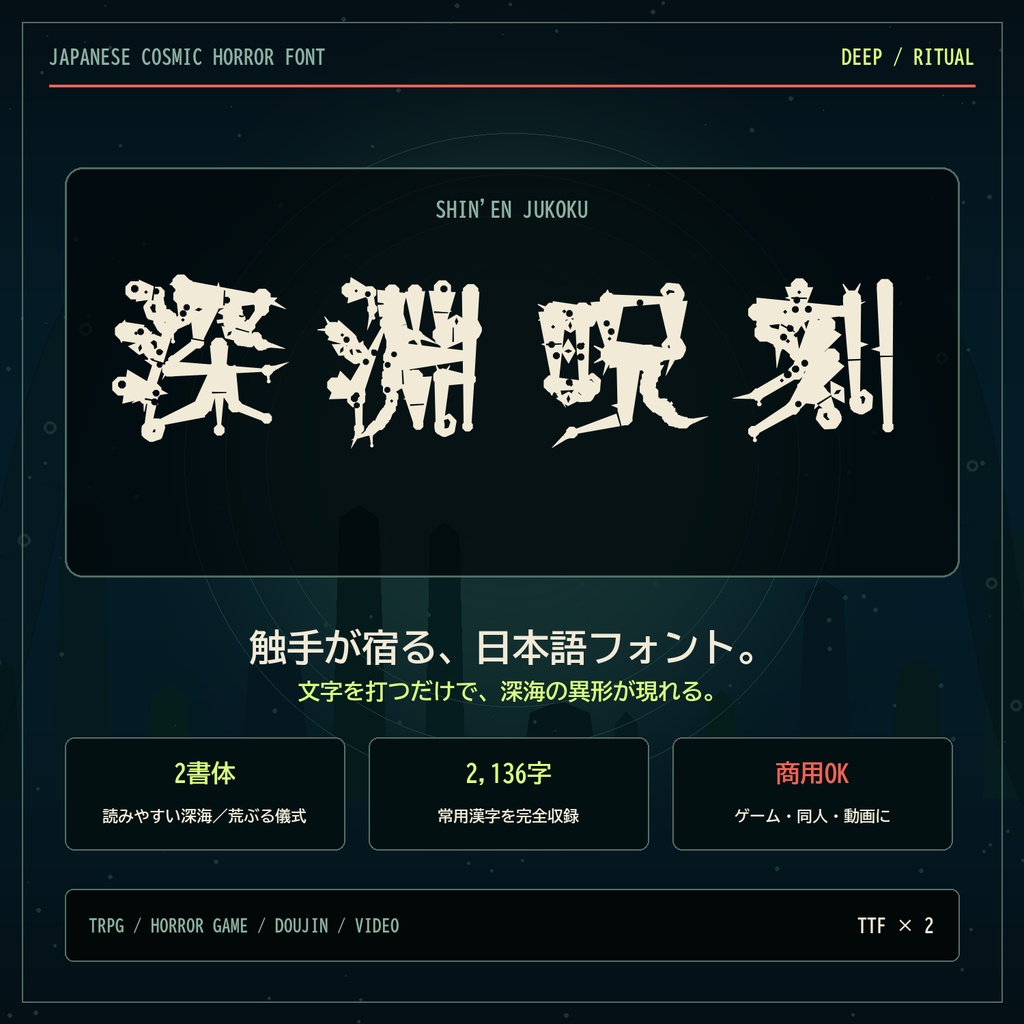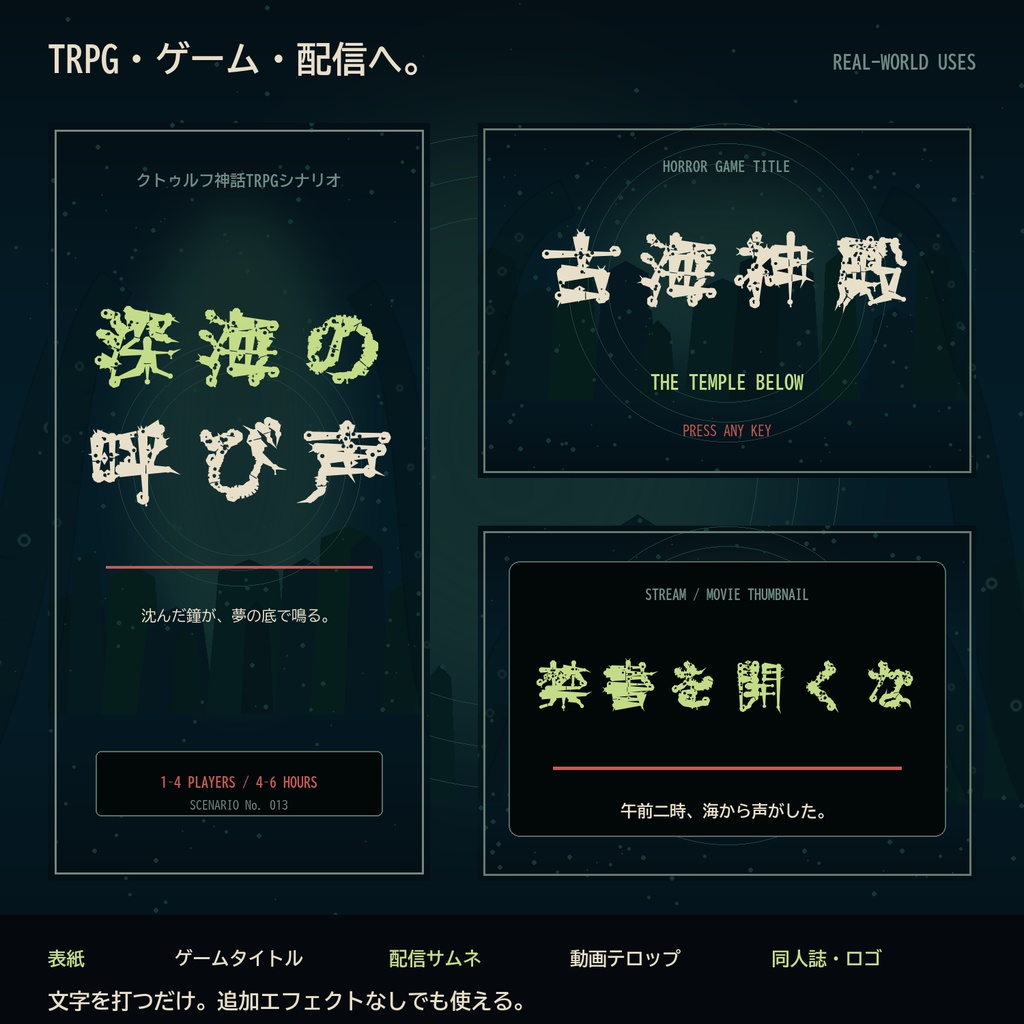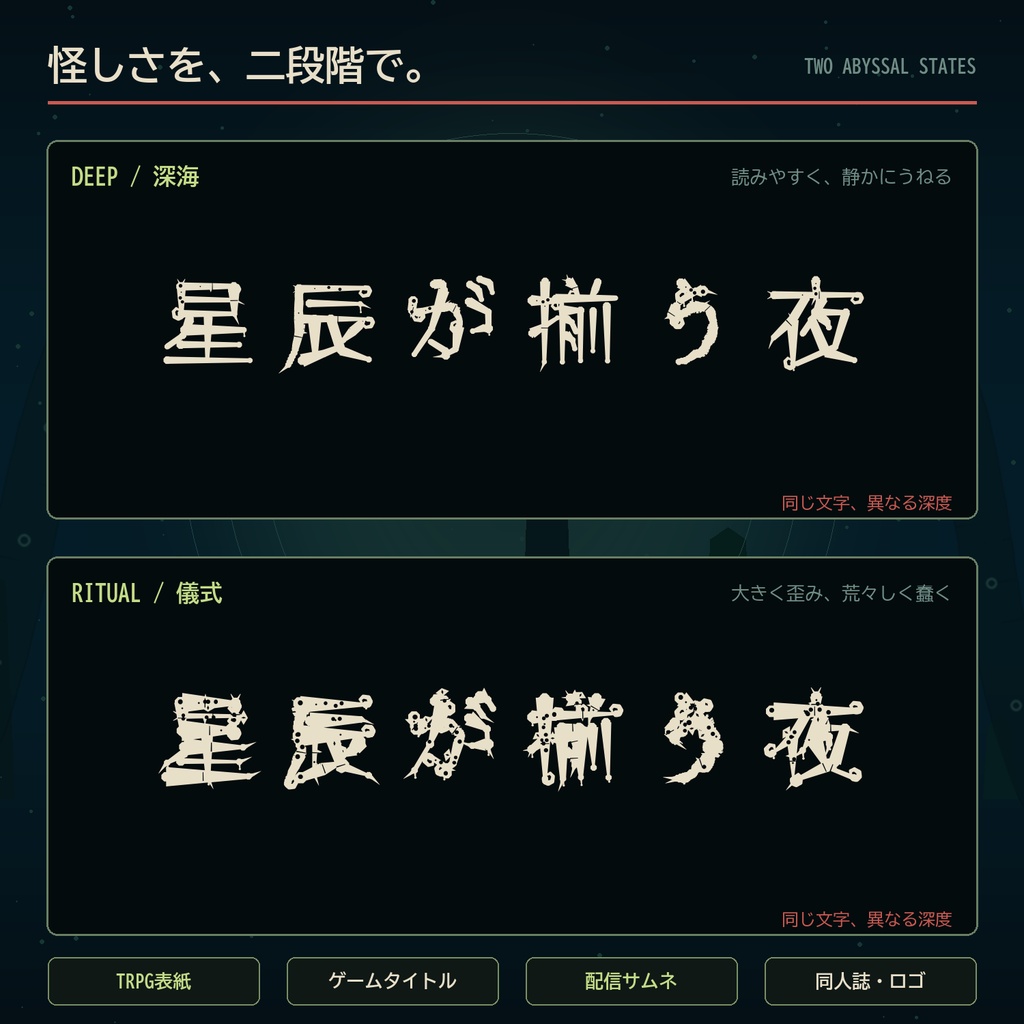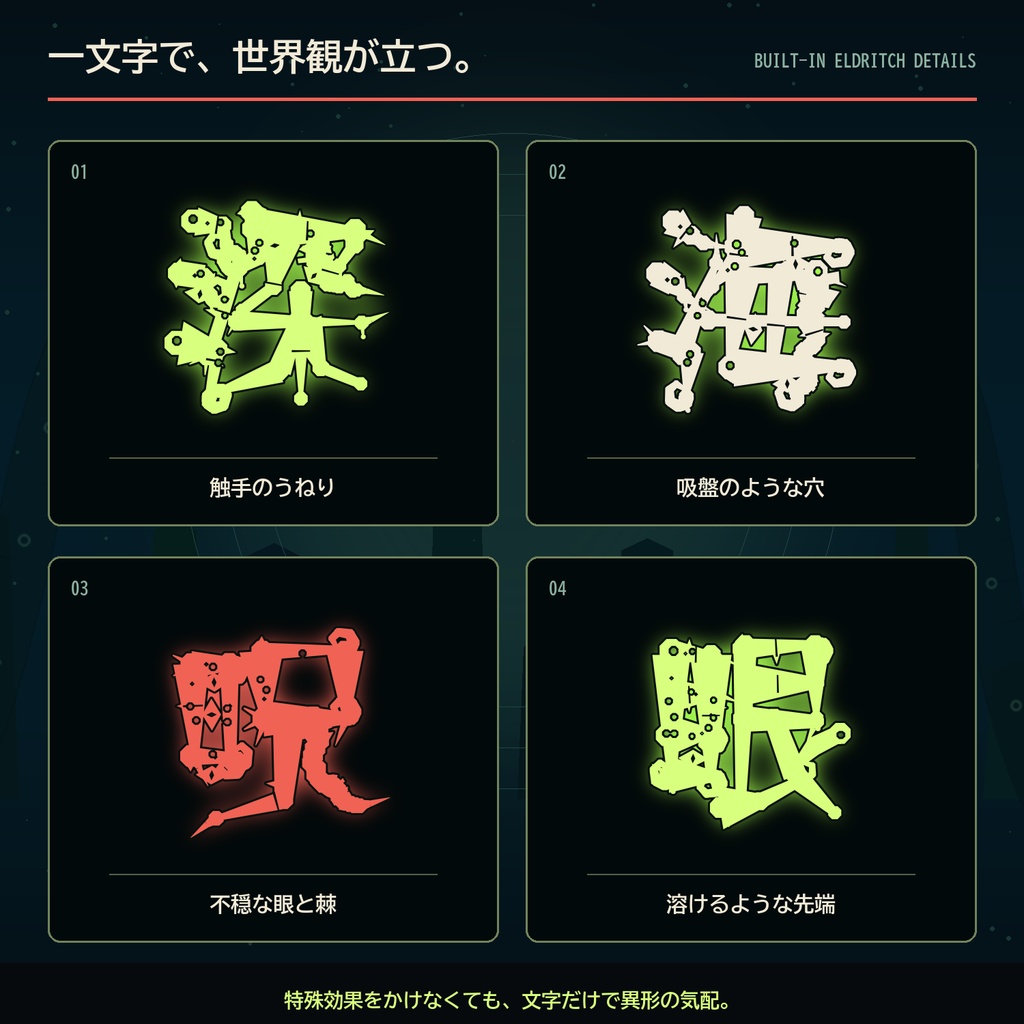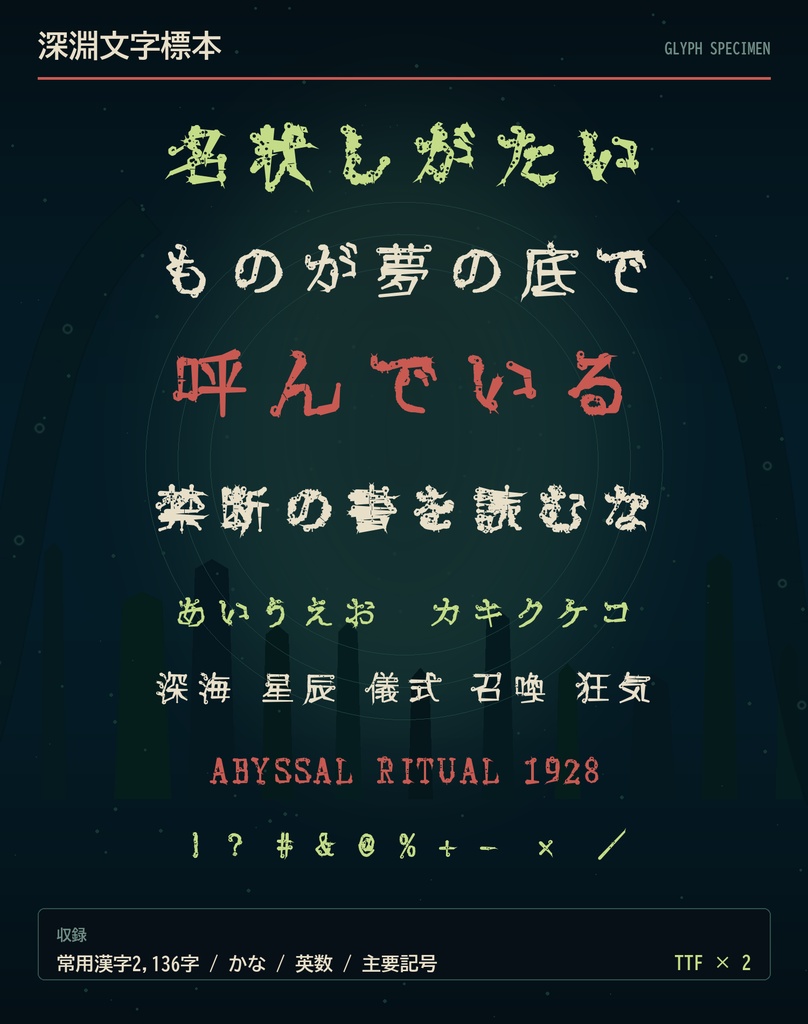
【クトゥルフ神話/TRPG】深淵呪刻|触手が宿るホラー日本語フォント・2書体
文字を打つだけで、深海の異形が現れる。 クトゥルフ神話TRPG、ホラーゲーム、配信サムネのための日本語フォント。 読みやすいDeepと、荒々しく蠢くRitualの2書体を収録しました。 「深淵呪刻(しんえんじゅこく)」は、文字そのものに触手のうねりと異形の気配を宿した日本語ディスプレイフォントです。不規則に脈打つ線、鋭く伸びる先端、巻き付く触手、吸盤穴、眼球紋、粘液、棘、裂傷を組み込み、文字を打つだけでクトゥルフ神話・コズミックホラーの世界観を作れます。 ■ 収録書体 ・Deep / 深海 読みやすさを残しながら、線のうねりと触手の気配を加えた見出し向け。 ・Ritual / 儀式 文字を大きく歪ませ、触手、吸盤、眼球紋、粘液、棘、裂傷を盛り込んだロゴ・表紙向け。 ■ 特徴 ・常用漢字2,136字 ・ひらがな、カタカナ、英数字、全角英数字、主要記号 ・TrueType形式(TTF)2書体 ・縦書きメトリクス収録 ・個人・商用利用可、クレジット不要 ■ 想定用途 クトゥルフ神話TRPG / ホラーTRPG / シナリオ表紙 / 配信サムネイル / ホラーゲーム / ダークファンタジー / 魔導書 / 同人誌 / ロゴ / 動画テロップ / ジャケット ■ 推奨サイズ Deep:24px以上 Ritual:36px以上 ■ ご注意 本商品はクトゥルフ神話・コズミックホラーを着想源としたオリジナル書体です。特定のゲーム、出版社、作品の公式商品ではありません。本文向けではなく、見出し・ロゴ向けの装飾書体です。細い吸盤や刻印は小サイズで潰れる場合があります。 ■ 利用条件 個人・商用を問わず、画像、映像、印刷物、ゲーム、Web画像、同人作品、ロゴへ利用できます。クレジット表記は不要です。フォントファイルそのものの再配布・共有・譲渡・転売、改変フォントの配布・販売、第三者が取得できる状態での公開は禁止です。詳しくはZIP内の「ご利用規約.txt」をご確認ください。